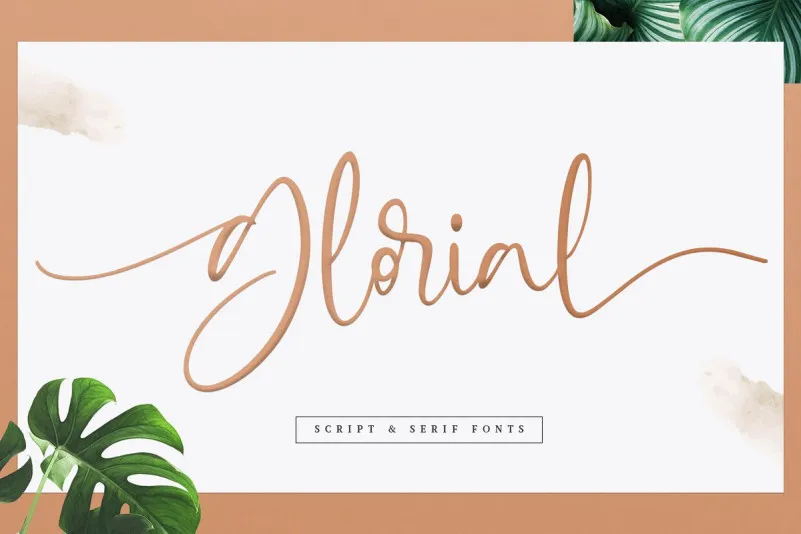
Descubra a Glorial Font Duo, uma elegante e moderna tipografia script criada pelo Runsell Studio. Esta fonte está pensada para oferecer um equilíbrio entre estilo clássico e contemporaneidade, adaptando-se perfeitamente com as serifas modernas e o giro. A Glorial Font Duo é uma versão dupla da Glorial Script, que combina a mão-dupla do tipo com linhas seriais modernas. Ela inclui letras maiúsculas e minúsculas completas, contando com swashes de início e fim para um toque mais natural. Também traz alternativas contextualizadas para as letras minúsculas, otimizando a legibilidade e criando uma fluidez incrível ao escrever. Ouça a Glorial Font Duo chamando-se Bohemian Melody, oferecendo swashes que se encaixam perfeitamente com as serifas modernas. As 50+ ligaturas presentes na fonte adicionam um toque natural e sofisticado à sua composição. Descubra a Glorial Font Duo e transforme suas criações em algo mais belo e realista, ao mesmo tempo que mantém seu próprio estilo único. Esta é uma adição perfeita para qualquer designer de gráficos ou designer de marca.